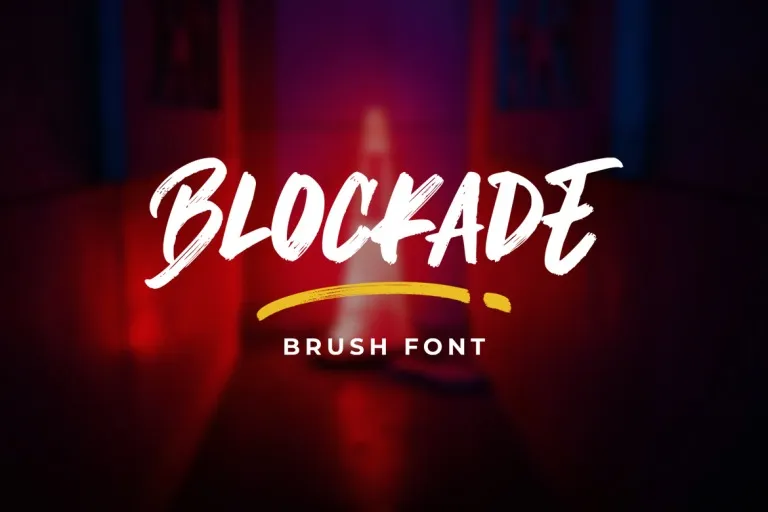
Blockade Font – Download Grátis
A Blockade Font é uma opção divertida para projetistas que buscam uma tipografia inspirada nas letras escritas no quadro negro. Seu estilo único e cool pode ser combinado com qualquer ornamento que você desejar, tornando-a perfeita para diversas aplicações de design como roupas, capas de livros, marcas na web, camisetas, embalagens e identidade visual. Uma característica especial desta fonte é o sobrenome “sweep bonus”, uma linha extra que pode ser integrada à sua criação de forma perfeita para um toque final. A Blockade Font é uma opção fácil de usar, facilitando a implementação em projetos e garantindo resultados incríveis. Se você está procurando por uma fonte divertida e versátil para seus trabalhos futuros, a Blockade pode ser a escolha perfeita.